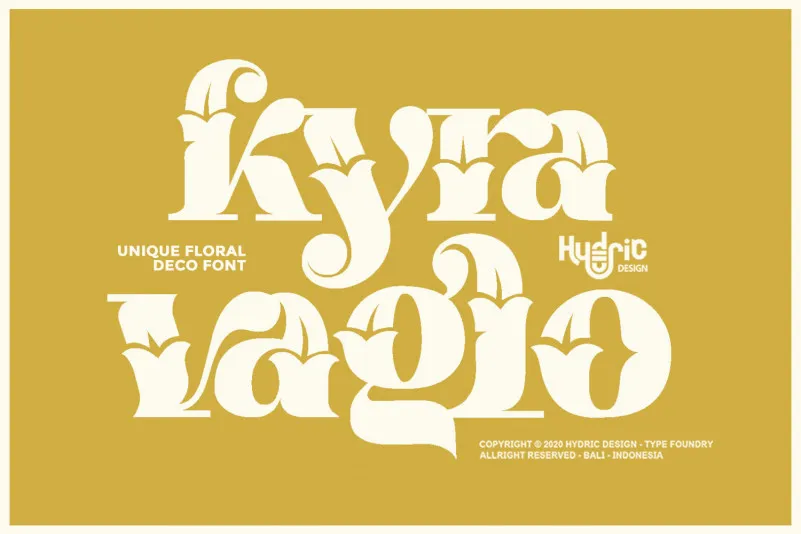
A fonte Kyra Vaglo é uma criação única que se inspira na flor asiática conhecida como Pétalas do Sótinho-de-Urso, ou mais popularmente como cebola-sapo. Inspirada por esse belo ornamento floral, a fonte Kyra Vaglo tem um design elegante e versátil, perfeita para uma ampla gama de projetos. Seja para criações visuais criativas como logotipos, cartões de convite para casamentos, seções de cabeçalhos de sites ou materiais impressos, etiquetas de embalagem, até mesmo camisetas personalizadas, Kyra Vaglo é um recurso gráfico que oferece opções incríveis e uma diversidade sem igual. Essa fonte ideal para quem busca adicionar um toque único e artesanal a qualquer projeto visual. Crie algo verdadeiramente especial com a Kyra Vaglo Font da HydricDesign.